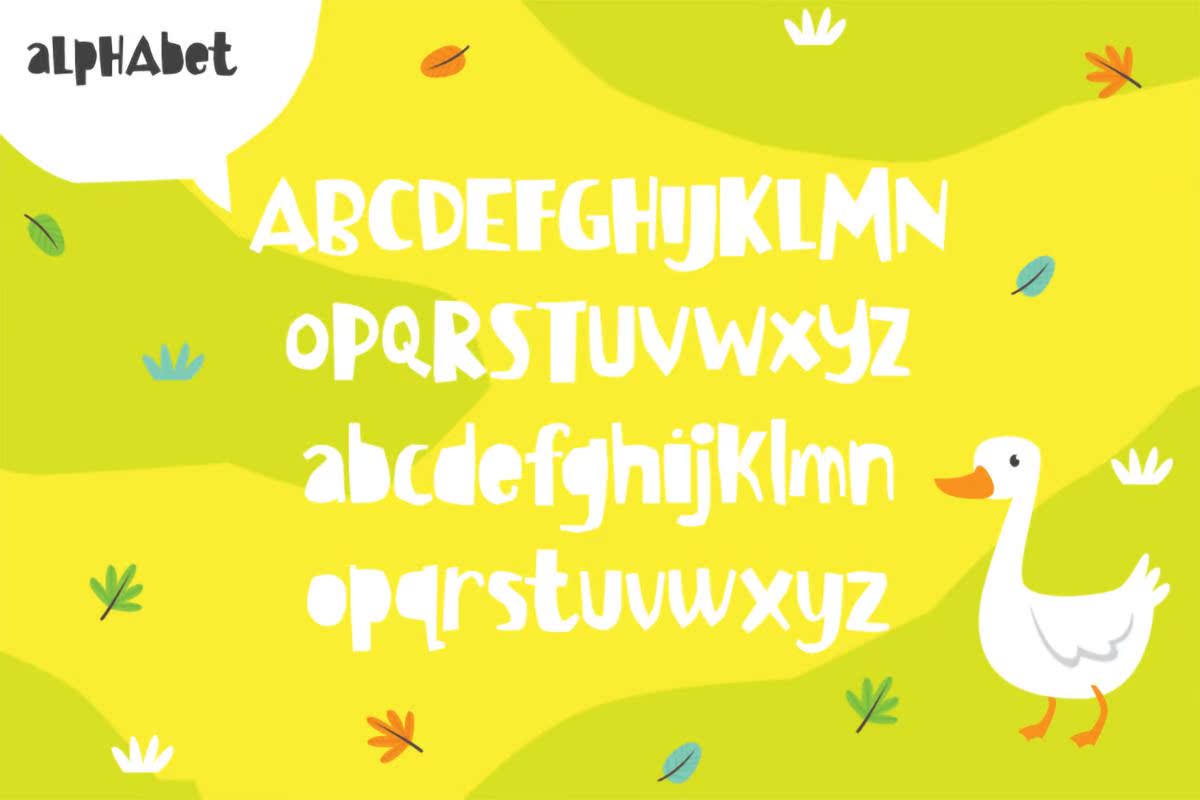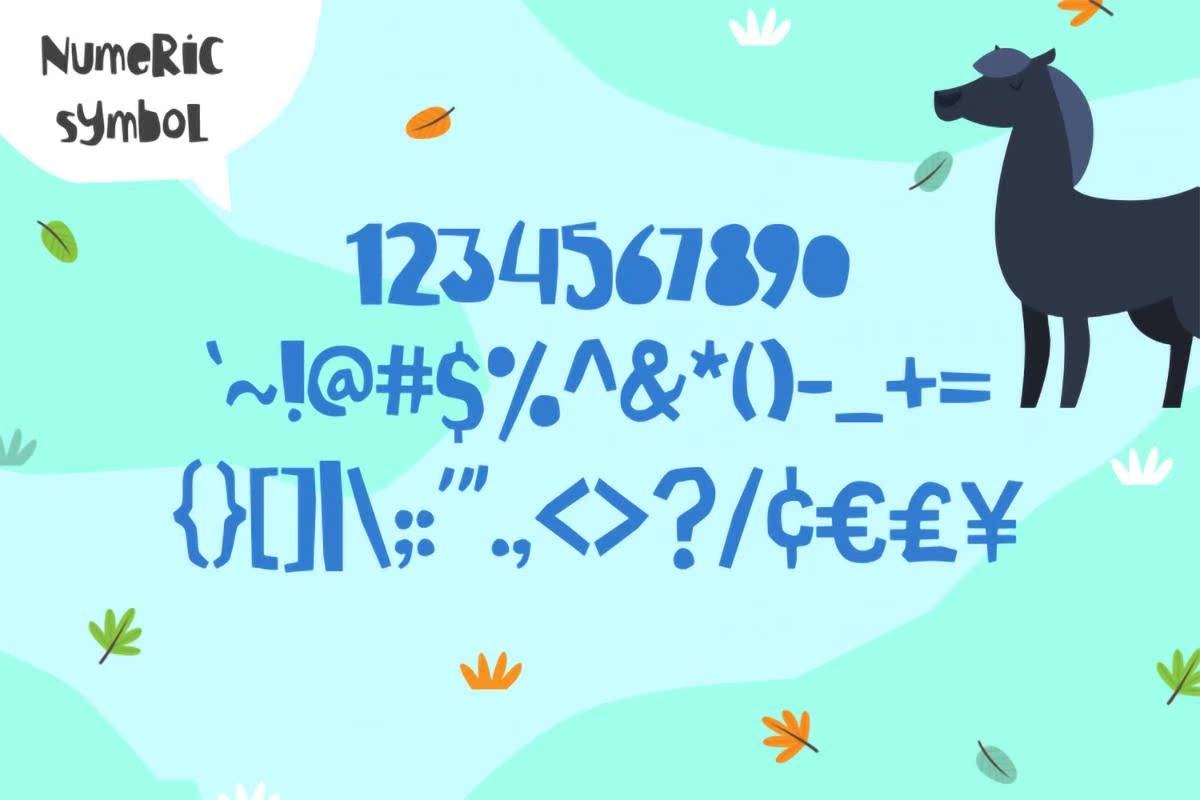
FreeDemobowReghulDisplayFontIsabeautifuldDisplayFontIsplayFont。它是一种可代表儿童最新信息的字符字体。此字体非常适合您的作品,如新书、小说、儿童读物、童话、木偶、动画书等。可用于格式文件,您可以轻松安装到任何设备上。但是,此免费字体仅适用于个人使用许可证。但是,首先购买PremiumVersion,您可以获得更多功能。